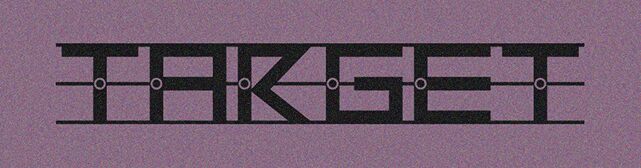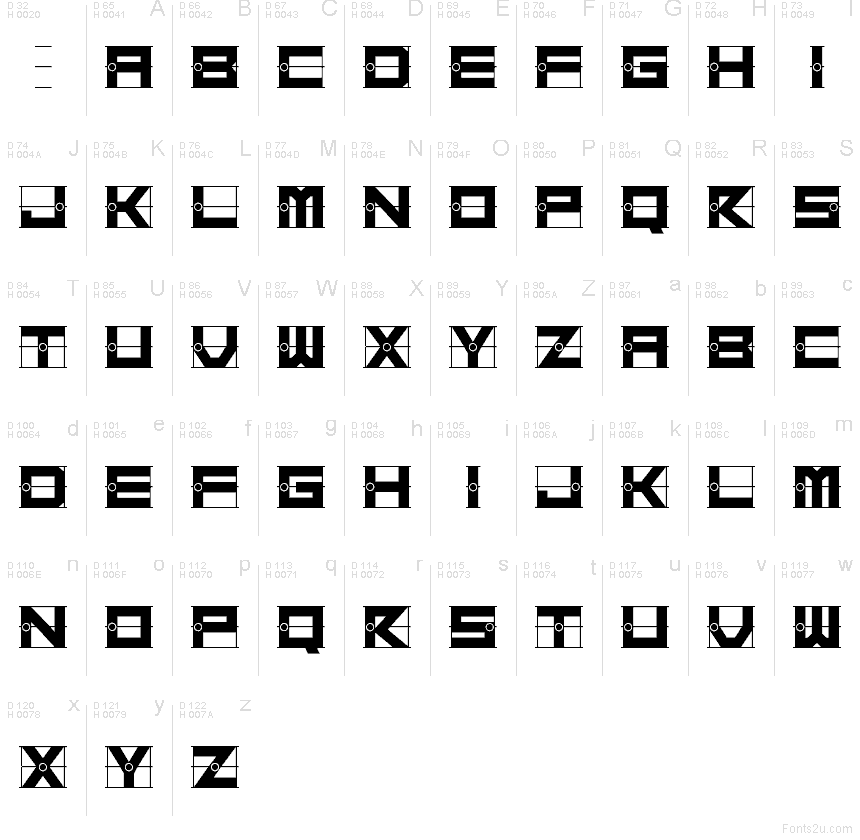
Target Kosovo od Vladimira Nikolića je bezplatné techno písmo typu display, ktoré pripomína sci-fi nápisy a modulárne ovládacie panely. Veľké písmená sú zostavené z pevných geometrických blokov, rezaných diagonál a opakujúcich sa kruhových bodov, ktoré fungujú ako vizuálne spojovníky. To dodáva písmenám zakódovaný rytmus, namiesto plynulej textúry písma.
Prirodzene zapadne do názvov hier, titulkov na plagátoch, hudobných obalov, grafiky pre streamerov a úvodných titulkov, kde je potrebné bezplatné písmo s ostrým, syntetickým výrazom. Použite ho tam, kde záleží na krátkych slovách – segmentované tvary a opakujúce sa kruhové značky robia z tohto písma presvedčivú voľbu pre logá, názvy frakcií a branding v štýle rozhrania.
Prezentácia a vizuálna ukážka písma Target Kosovo Regular
Mapa znakov písma Target Kosovo Regular
Mapa znakov písma Target Kosovo Regular: Základná latinka, strana 1
Glyfy písma Target Kosovo Regular — Základná latinka, strana 1